語りかける声としての文字
一杯のコーヒーを通じて人の心を豊かにするというミッションを掲げ、世界66カ国に2万を超える店舗を展開するスターバックス。その日本法人であるスターバックスコーヒージャパン株式会社は、日本語表記に用いるコーポレートフォントとしてAXIS Fontを採用し、店内のポスターやメニュー、パンフレット、Webなど、幅広い媒体で活用しています。
スターバックスのコミュニケーションでは、多くの場合、飲み物やフードのビジュアルがメインであり、文字は主役ではありません。また、英語と日本語の併記が基本となります。このため日本語フォントには、強い個性を主張するのではなく、ビジュアルにすっと溶け込めること、英文とバランスよく共存できることが求められました。同社のクリエイティブスペシャリスト河上聡氏は次のように語っています。
「クリエイティブを表現するにあたっては、ワールドワイドのガイドラインが存在し、Avenir (アヴェニール) など主に使用する3種類の欧文フォントが定められています。加えて、スターバックス店内などでご覧になったことがあるかと思いますが、ハンドグラフィティ (手書き)もフォントではありませんけれど、指定書体のひとつとなっています。
個々の制作物では、伝えたいメッセージに合わせ、そのなかから最適な書体を選んで使用するわけです。これらの欧文書体のどれと組み合せてもしっくりくる日本語書体として採用したのが、AXIS Fontです」
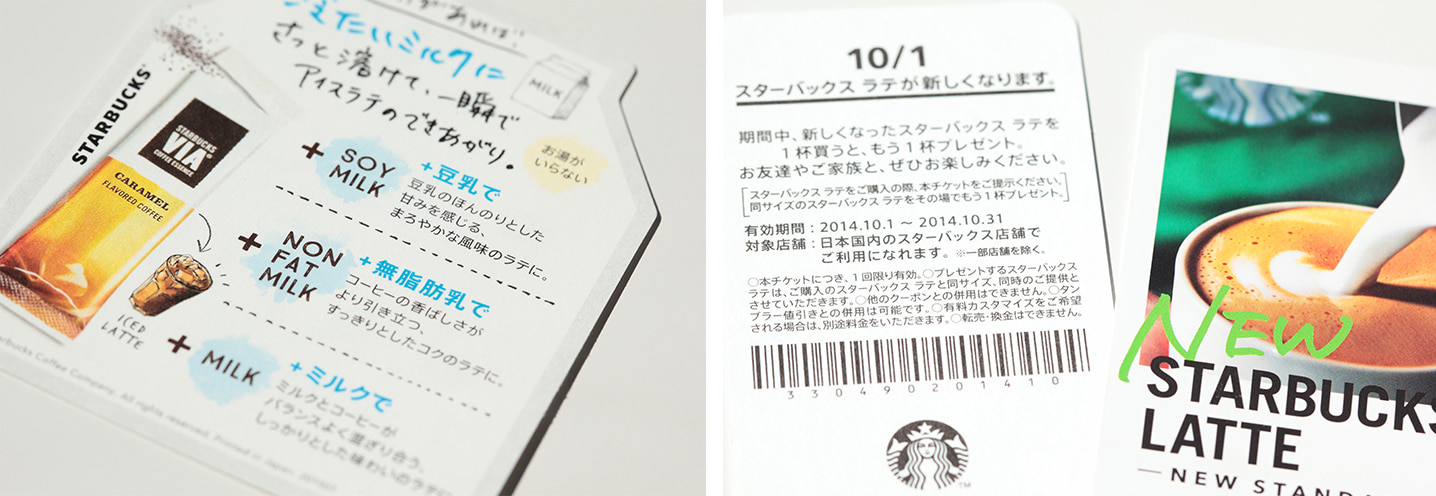
日本語書体の選定にあたって行われた他のフォントとの比較・検証では、英語のメッセージとぶつかり合わない、組み上がったときに違和感がないという点で、AXIS Fontのアドバンテージが確認されました。また、欧文書体によって日本語書体を使い分けるというシステムも検討されましたが、そうすると日本語書体のデザイン上の主張が見えてしまい、ブランドとして伝えたいことがブレるという理由から、結果としてAXIS Fontひとつに絞られることとなりました。
「単にコーヒーを提供するのではなくて、人の心を豊かにするために何ができるのかという点について、僕たちは日々知恵をしぼっています。ですから、たとえばアイキャッチ的なコピーを開発しようとは思いません。誇張や煽るような表現はしたくないのです。ポスターやパンフレットなどでも、お客様に敬意と親しみを込めて直接語りかけているような、人間味あふれるコミュニケーションを目指しています。そのときに、僕たちからのお客様へのメッセージを伝える声として、AXIS Fontはまさにうってつけだと感じています」